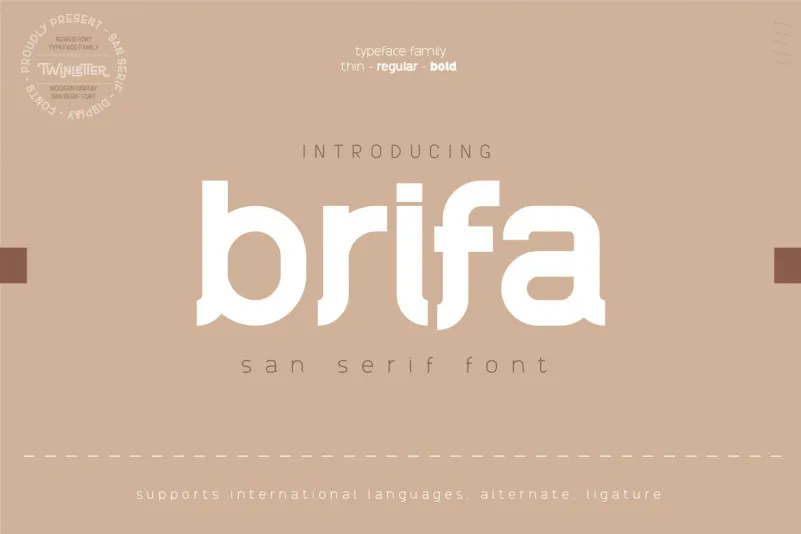
Brifa Font – Download Grátis
A fonte Brifa Font é perfeita para designers que procuram uma mistura única e moderna, capaz de dar um toque diferenciado a qualquer projeto visual. Seu design sem serif oferece uma textura suave e limpa que se ajusta perfeitamente a várias categorias de projetos, incluindo eventos esportivos, marcas e logotipos, banners, cartazes, títulos cinematográficos, embalagens de alimentos e bebidas, tecnologia, nomes de produtos e até mesmo roupas. Este font é um recurso valioso para qualquer designer que está sempre em busca de novas maneiras de expressar sua criatividade, seja através do design gráfico ou publicitário. Não importa o projeto, a Brifa Font tem a capacidade de fazer seu trabalho de forma profissional e atraente.